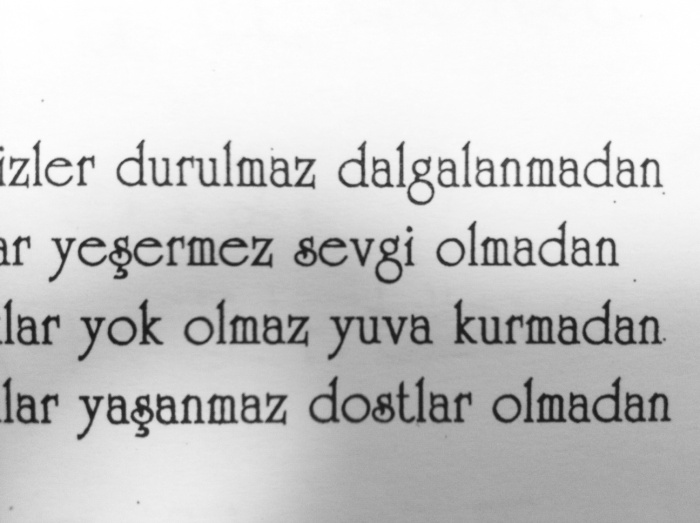
Ein Bauer Bodoni mit ein wenig Upper East Side?!
Bin auf der Suche nach einer Schrift, welche eine Mischung aus einer Bauer Bodoni und diesem Free-Font UpperEastSide zu sein scheint, also etwas schmaler als die Bodoni läuft und außerordentlich große Teile der Punzen hat (explizit betrifft das den d oder g).
Kann jemand helfen?
Hat aber nicht so viel mit Bodoni am Hut, ist von der Kontrastart her eher eine konstruiert anmutende Renaissance-Antiqua und hat klassische Proportionen (kreisförmiges o).
… Kontrastart …
Ein tolles Wort, aber das nur nebenbei. Ich hab jetzt drei Mal Kontra-Start gelesen … ;-)
Was ist eine Kontraftart?
Nebenbei, bei wem es inhaltlich nicht eh unmittelbar geklärt ist, bei dem herrscht spätestens beim Artikel schon Eindeutigkeit.
Weiß jetzt nicht, ob es die feine Art ist es jetzt zu zitieren, wenn er scheinbar doch nicht mag, daß es da steht.
Aber ich denke man kann es sich denken ...  ;-)
Das ist schon klar; ich wollte den Beitrag unmittelbar nach dem Absenden löschen, weil er fehlerhaft war. Den Begriff »Ausblenden« habe ich nicht für voll genommen bzw. konnte ich nicht einordnen.
Wir müssen also nicht nur das Lang-ſ wiederbeleben, wir brauchen auch noch ganz andere typografische Ausdrucksformen, um verständlich zu schreiben:
Das ſ iſt in dieſem Falle ja nicht erhellend, aber ſmall caps wie in 5. wäre mal eine feine Anwendung für dieſe.
Nur blöd, wenn Groß- und Kleinbuchſtabe die gleiche Grundform haben wie beim s, dort iſt das ſ weiterhin nötig.
Wachſtube
WachsTube